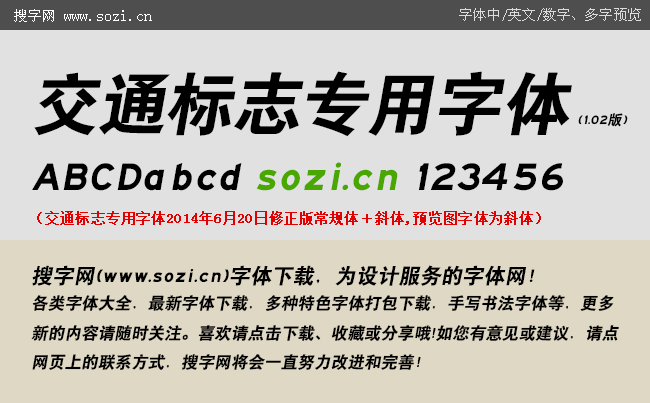
交通標(biāo)志專(zhuān)用字體常規(guī)體和斜體
搜字網(wǎng)提供一款交通標(biāo)志專(zhuān)用字體常規(guī)體和斜體中文字體下載,交通標(biāo)志專(zhuān)用字體是一款應(yīng)用于交通標(biāo)志的專(zhuān)用黑體,結(jié)構(gòu)端正、重心平穩(wěn)、美觀實(shí)用,并配有斜體效果,適用于包裝印刷、廣告設(shè)計(jì)、平面設(shè)計(jì)、書(shū)籍報(bào)紙等領(lǐng)域。
• 風(fēng)格類(lèi)別: 黑體